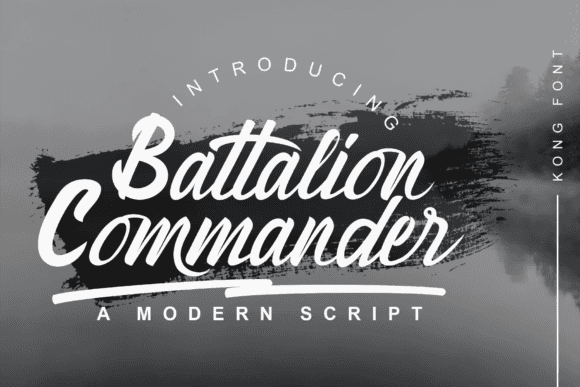
Fuente Battalion Commander para proyectos de manualidades, logotipos e impresión
Comandante del batallón Font
Battalion Commander es una fuente manuscrita moderna y cursiva, perfecta para artesanos y diseñadores. Es compatible con herramientas de diseño populares como Photoshop y Silhouette Design Studio, lo que la hace versátil para diversos proyectos creativos. Su estilo alegre añade un toque único a tus diseños, ya sea para uso personal o profesional.
Reflejos:
- Estilo moderno, cursivo y manuscrito
- Ideal para artesanos y diseñadores.
- Perfecto para proyectos creativos.